Highlights der Laura Worthington.
Laura Worthington.
Laura Worthington ist eine Schriftart-Designerin, die in der Nähe von Seattle, Washington lebt. Nach ihrer Ausbildung und Arbeit als Grafikdesignerin hat sie ihre lebenslange Faszination für Schriften und Typographie umgesetzt und ein Unternehmen dafür gegründet. Ihre erste Schriftart erschien im Jahr 2010. Ihre Fertigungsanlage, die sie selbst betreibt, hat seitdem mehr als 100 Schriftarten veröffentlicht und individuelle Schriftdesigns für bekannte Marken erstellt, darunter Microsoft, Smuckers und das St Jude Children’s Hospital, sowie für die weltweit größten Verlage. Lauras Schriftarten konzentrieren sich auf Kalligraphie für Displays und beinhalten viele dekorative Elemente wie Schwünge, Rahmen, Banner und clevere Alternativen für jeden Kontext. Lauras Designs wurden bereits mit Dutzenden brancheninternen Preisen ausgezeichnet und waren in Publikationen wie Communication Arts, HOW, Letter Arts Review, Computer Arts und CreativePro zu sehen.
Adorn
Adorn ist eine offene und freundliche Schriftart, die dem seriösen Aussehen formeller Einladungen im geschäftlichen Kontext einen modernen Schliff verleiht. Die Schriftfamilie aus handgezeichneten Schriftarten bietet Designern eine atemberaubend große Auswahl. Die Schriftarten harmonieren trotz ihrer Unverwechselbarkeit zusammen. Adorn beinhaltet sieben Display-Schriftarten, vier Schreibschriften, Monogramme, Ornamente, Illustrationen, Banner, Rahmen und Schlagworte.
Ed's Market
Ed’s Market bringt den warmen, einladenden Vibe klassischer Konsumposter aus dem 20. Jahrhundert und Schriftarten wie auf einer Speisekarte. Diese handgezeichnete Schriftartenfamilie sorgt für ein solides Repertoire im Stil von Vintage-Schildern. Jede Schrift ist unterschiedlich, aber wurde klar von derselben Hand erstellt. Jede Display-Schrift bietet drei Varianten von jedem Buchstaben, was bei mehrmals vorkommenden Buchstaben für einen handgezeichneten Look sorgt. Ed‘s Market beinhaltet drei Schriftarten, jede mit mehr als 100 alternativen Zeichen und Formen. Zu den Designelementen gehören expandierbare Pfeile, Linien und Schleifen sowie Abzeichen, Schwünge und Wolken.
Beloved
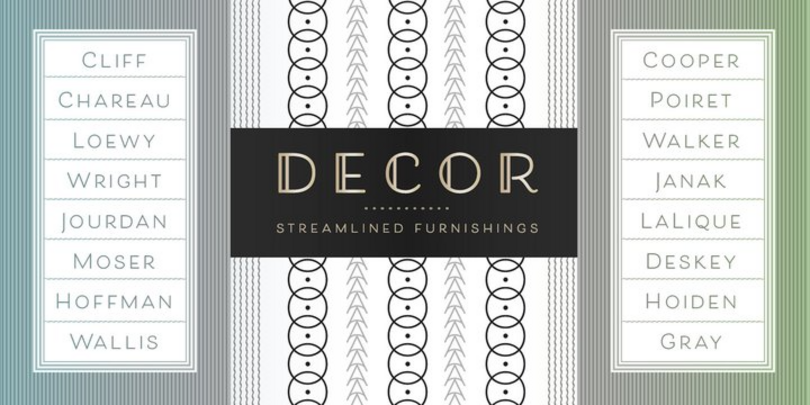
Die Beloved-Kollektion kombiniert eine lebhafte Schreibschrift, eine elegante, vielseitige serifenlose Schriftart und 80 Dekoelemente, um romantische Stimmung zu verbreiten. Beloved Script ist eine lässige, natürliche Handschrift. Hierbei handelt es sich um eine halb zusammenhängende Schreibschrift mit einfacher Strichstärke, die an die klassische Schriftkunst des 20. Jahrhunderts mit Kugelschreiber oder runder Feder erinnert. Beloved Sans, eine einfache serifenlose Schrift, besteht nur aus Großbuchstaben mit zugehörigen Kleinbuchstaben, die 85 % kleiner sind – genug Unterschied, um in Texten wahrgenommen zu werden. Die Titelvariante überzeugt durch einen Hauch Art Deco, und die Großbuchstaben sorgen für kalligraphischen Flair. Beide sind sehr schwungvoll und liefern Alternativen, ideal für Wortmarken und auffällige Überschriften.
Fairwater
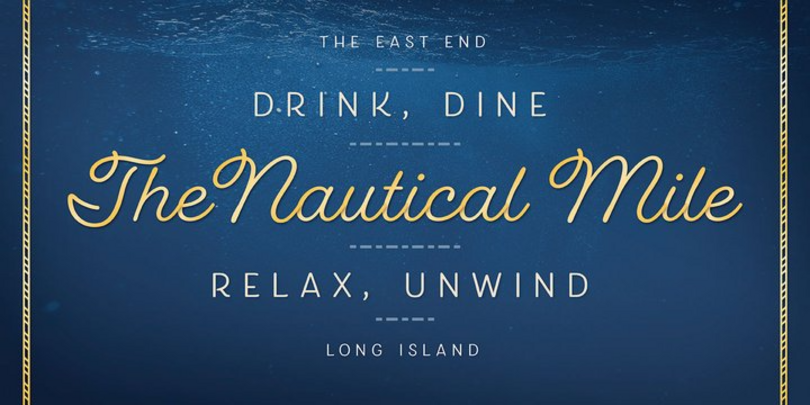
Der Stil von Fairwater erinnert an die Schreibschrift Anfang bis Mitte des 20. Jahrhunderts, die vereinfachten, nachsichtigen Tattoo-Schriftarten und die Bildthemen aus Seemannstätowierungen Anfang bis Mitte des 20. Jahrhunderts. Die Fairwater-Familie beinhaltet eine Schreibschrift und eine serifenlose Schriftart in drei Stärken, vier dekorative serifenlose Schriften und eine sehr dekorative Schriftart, DIY Lines, die auf nautische Motive anspielt. DIY Lines besteht aus 250 Ornamenten – Schiffe, Anker, Ruder, Knoten, Seile, Pflanzen, Diamanten, Pfeile und mehr. Die Fairwater-Familie beinhaltet außerdem eine große Auswahl an Schwüngen und Alternativen.
Charcuterie
Charcuterie ist eine Kollektion aus zehn unterschiedlichen, aber verwandten Schriftarten, mit Optionen für Gravuren, Kursiv, Deco und Blockschrift sowie drei dekorativen Schriftarten. Die Schriften können einzeln oder in Kombination mit anderen eingesetzt werden. Charcuterie-Elemente eignen sich für Überschriften, Titel, Logos, Displays, Verpackungen, Schilder oder Werbeanzeigen. Die gesamte Kollektion ermöglicht Experimente und ist eine wahre Schatzgrube, die für maximale Vielseitigkeit sorgt.
Samantha Script
Samantha ist eine fröhliche, ansprechende Schreibschrift, die auf Federschriften basiert und sich durch leicht komprimierte Zeichen und einen wohlüberlegten Rhythmus auszeichnet. Samantha gibt es in Gerade oder Kursiv, jede mit normalen und dickeren Stärken. Die über 1.100 Alternativen und Schwungbuchstaben sind unterschiedlich groß und komplex. Samantha beinhaltet 60 Ornamente und 45 Schlagworte, Tabellenziffern sowie geschwungene Ziffern und Ziffern im alten Stil.
GrindelGrove
GrindelGrove ist eine gruselige Schriftart, die an dunkle Wälder, lang verloren geglaubte Schatzkarten und unheimliche Geschichten erinnert. Die rindenartige Textur und v-förmigen Buchstaben verbreiten eine unheimliche Atmosphäre – eine perfekte Ergänzung für Gruselgeschichten, Geisterbahnen und seltsame Ereignisse. Der dramatische Charakter der Schriftart macht, dass sie besonders gut für Überschriften und kurze, schlagkräftige Aussagen eingesetzt werden kann. Auch wenn es zunächst so aussieht, als würde sich GrindelGrove nur für Halloween und ähnliche Gruselmomente eignen, passt die Schriftart zu erstaunlich vielen Kontexten. Der Designer hat sie sogar ursprünglich für eine Broschüre über Gärten mit einheimischen Pflanzen kreiert.
Boucherie
Die Schriftart Boucherie fängt die lebhafte Essenz der Werbetypografie im Frankreich des 19. Jahrhunderts ein und verbindet sie mit neuen Designs. Designer können diese Schriftart einsetzen, um Kompositionen zu kreieren, die gleichzeitig neu und vertraut sind. Boucherie liefert vier unterschiedliche Display-Schriftarten – plus Ornamente, Schlagwörter und Rahmen – die alle perfekt zueinander passen.
Nelson
Die gravurartigen Großbuchstaben, durch die sich Nelson auszeichnet, erinnern an den Wilden Westen und Farbe auf verwittertem Holz. Designer können die Schriftart mit auffälligen und rauen Varianten kombinieren oder die Display-Schrift für Essensverpackungen, Speisekarten und Tourismusbeschilderungen nutzen.
Congenial
Congenial ist eine leichte Abweichung von Laura Worthingtons typischen Schriftarten, die von Kalligraphie geprägt sind. Sie ist eine serifenlose Schriftart, die eine schlichte, sehr gut lesbare Ergänzung zu den dekorativeren Schriftarten darstellt. Allerdings weist Congenial trotzdem einige kalligraphische Anspielungen auf, zum Beispiel handgemalte Elemente in den stärkeren Schriftbreiten. Die Schriften sehen freundlich und einladend aus und verfügen über eine großzügige x-Höhe und sehr differenzierte Zeichen.
Elaina
Die Schreibschrift Elaina Script ist klar und präzise. Dank ihrer Standartform, nüchterner Mittellänge und zurückhaltenden Ober- und Unterlängen ist sie auch auf kleineren Displays und in kurzen Textblöcken einfach zu lesen. Die Schriftart zeichnet sich durch Kleinbuchstaben aus, die nicht miteinander verbunden sind, durch stilistische Alternativen, und sie beinhaltet – wie die meisten Schriftarten dieses Designers – zahlreiche Schwünge, Alternativen und Ligaturen –optimal für auffällige Effekte in großer Größe und Markenauftritte. Die begleitende Schriftart, Elaine Semi Serif, überzeugt durch eine angepasste Strichstärke und leicht ausgestellten Abschlüssen. Sie verbreitet ein humanistisches Flair und verleiht jedem Auftritt Wärme und Positivität. Semi Serif eignet sich gut für den Textkörper und zusammenhängende Kontexte.